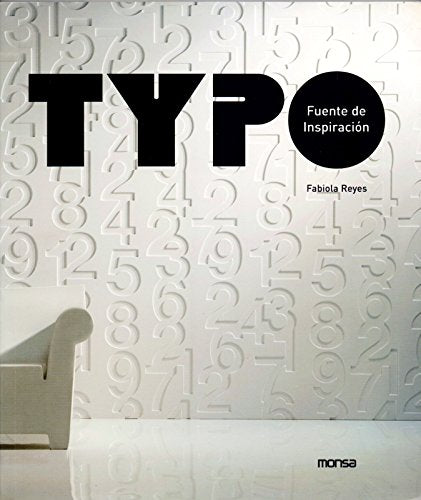
Detalles: TYPO, no es un libro de tipografía convencional, pretende ir más allá mostrando una variada selección de proyectos procedentes de distintos campos creativos como el diseño gráfico, la moda, la escultura , el diseño industrial y la arquitectura, entre otros, que artistas y diseñadores de diferentes partes del mundo han realizado a partir del uso y la experimentación con la tipografía.Muchos de los proyectos incluidos en este libro se han creado desafiando las barreras del diseño tipográfico para sugerir soluciones originales y alternativas y, de una forma más o menos evidente, para interactuar con el individuo y provocar en él, reacciones, sensaciones e incluso, sentimientos.Stefan Sagmeister, Andrew Byrom, Olga Adelantado, Catherine Griffiths, Borja Garmendia, Silvia B., Why Not Associates, Gordon Young, David Delfín y Pentagram son algunos de los artista invitados en este libro que demuestra que los límites entre el diseño, el arte y la tipografía no existen